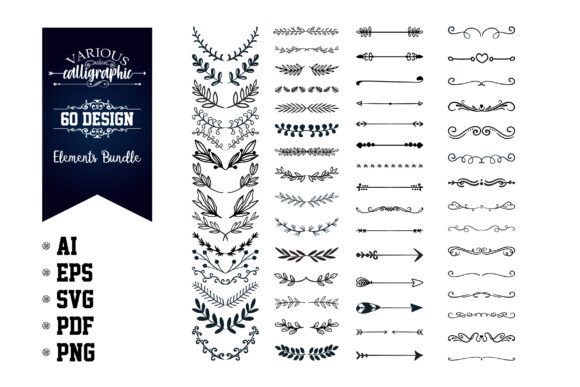
Various Calligraphic Design Elements Set
Doğru tasarım öğelerini bulmak zor olabilir, ancak Various Calligraphic Design Elements Set, çalışmanızı anında bir üst seviyeye taşıyan olağanüstü bir koleksiyon sunar.
Hassasiyetle hazırlanan Various Calligraphic Design Elements Set, temiz vektörler, pürüzsüz tipografi ve içinizin rahat etmesi için ticari bir lisans sağlar.
İster İsteğe Bağlı Baskı (POD) ürünleri, ister düğün davetiyeleri veya sosyal medya grafikleri oluşturuyor olun, Various Calligraphic Design Elements Set ideal bir uyumdur.